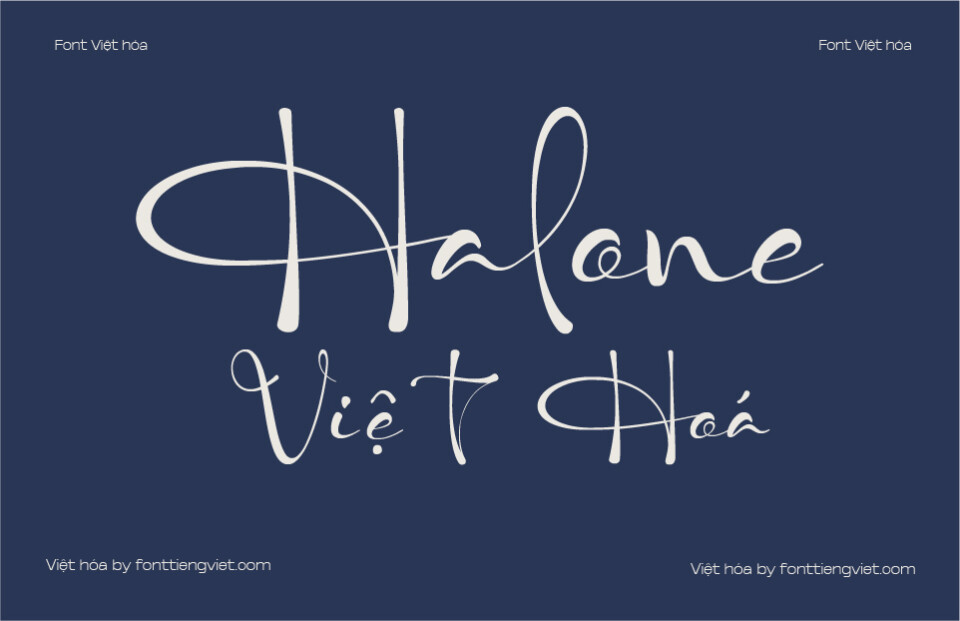
Font Việt hóa 1FTV VIP Halone – Lựa chọn hoàn hảo cho thiết kế học đường
Giới thiệu về Font Việt hóa 1FTV VIP Halone
Trong thế giới thiết kế đồ họa hiện nay, việc tìm kiếm một bộ Font Chữ vừa mang nét hiện đại, vừa giữ được sự thanh lịch là điều rất quan trọng đối với các bạn học sinh và giáo viên. Font Việt hóa 1FTV VIP Halone nổi lên như một giải pháp tối ưu, đáp ứng đầy đủ các tiêu chuẩn về thẩm mỹ và tính ứng dụng cao. Đây là bộ phông chữ được tinh chỉnh kỹ lưỡng, hỗ trợ đầy đủ bộ gõ tiếng Việt giúp người dùng dễ dàng thể hiện ý tưởng mà không lo lỗi hiển thị. Với đường nét mềm mại nhưng vẫn giữ được cấu trúc vững chãi, Halone mang đến cảm giác chuyên nghiệp cho mọi khung hình.
Ưu điểm nổi bật của bộ Font Việt hóa 1FTV VIP Halone
Thiết kế tinh tế và dễ đọc
Một trong những điểm mạnh lớn nhất của Font Việt hóa 1FTV VIP Halone chính là độ tương phản hài hòa giữa các nét thanh và nét đậm. Điều này giúp văn bản trở nên dễ đọc, phù hợp cho cả việc làm tiêu đề lẫn trình bày nội dung chi tiết trong các bài giảng hay báo cáo ngoại khóa. Sự chỉn chu trong từng ký tự giúp các thiết kế học đường trở nên bắt mắt và thu hút hơn bao giờ hết.
Ứng dụng đa dạng trong học tập
Bộ phông này cực kỳ linh hoạt, có thể sử dụng để làm thiệp mời, thiết kế bìa sách, hoặc tạo ra các slide thuyết trình ấn tượng. Nhờ tính năng việt hóa chuẩn, các em học sinh có thể tự do sáng tạo nội dung mà không gặp rào cản về ngôn ngữ. Đây thực sự là công cụ hỗ trợ đắc lực cho môi trường giáo dục sáng tạo.
Kết luận về bộ Font Việt hóa 1FTV VIP Halone
Việc sử dụng Font Việt hóa 1FTV VIP Halone không chỉ giúp nâng tầm giá trị cho các sản phẩm thiết kế mà còn tạo cảm hứng học tập và giảng dạy. Với sự kết hợp giữa nét đẹp truyền thống và hơi thở hiện đại, bộ phông này chắc chắn sẽ làm hài lòng những người dùng khó tính nhất. Hãy trải nghiệm ngay bộ Font Miễn Phí, Font Việt Hóa, Font Việt hóa 1FTV VIP Halone để biến những ý tưởng trên trang giấy thành những tác phẩm nghệ thuật độc đáo và ấn tượng trong tương lai.